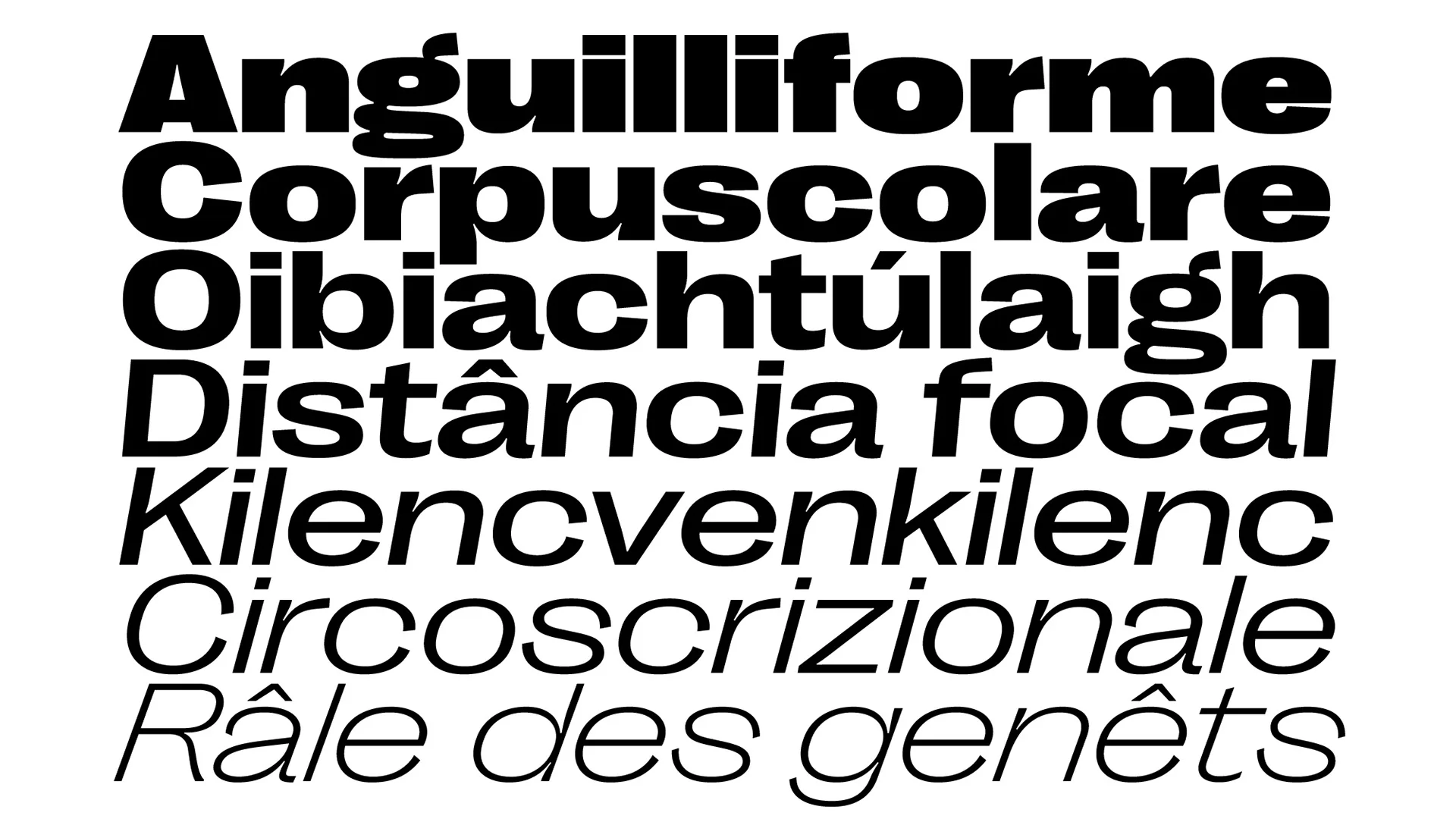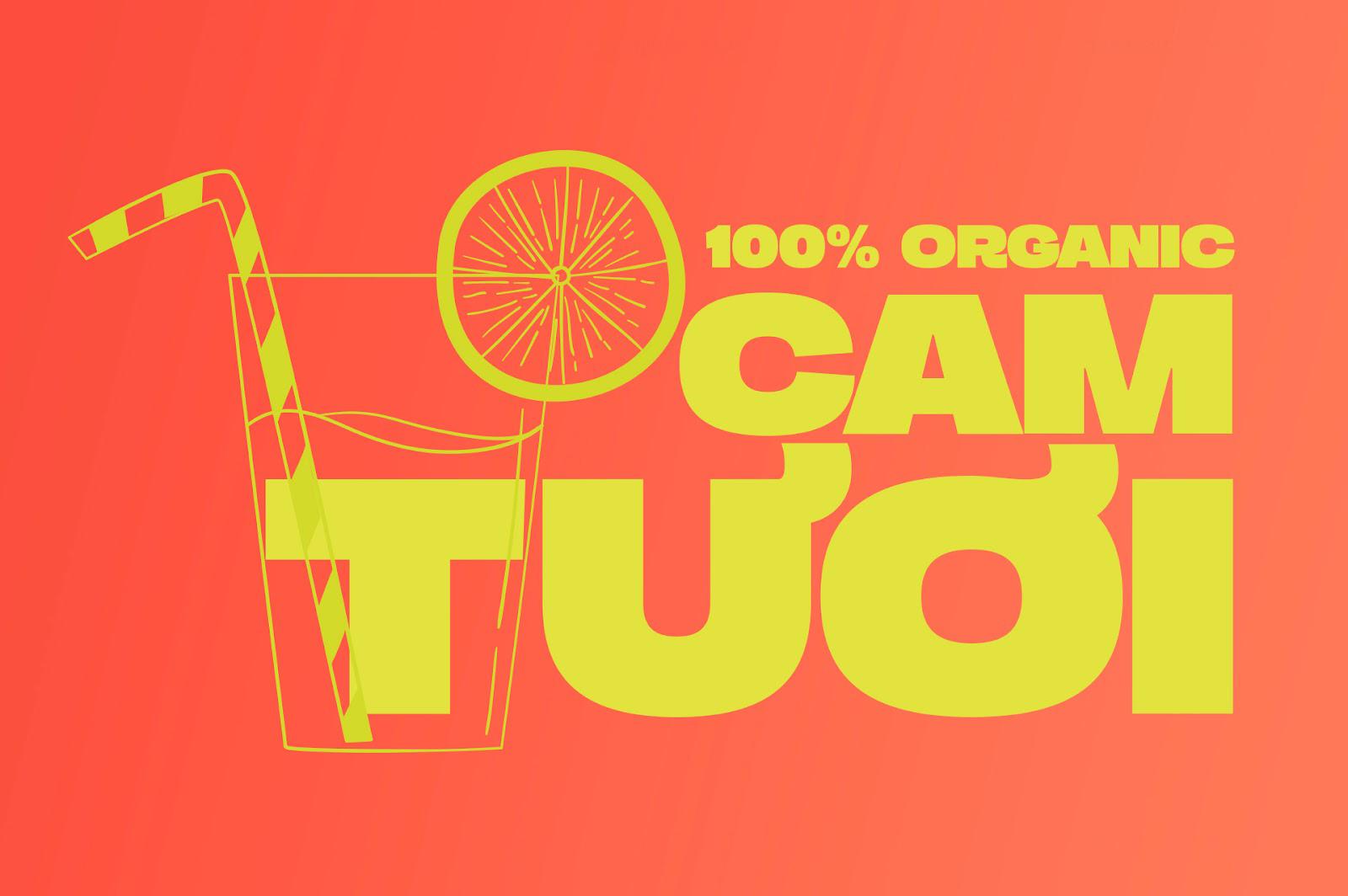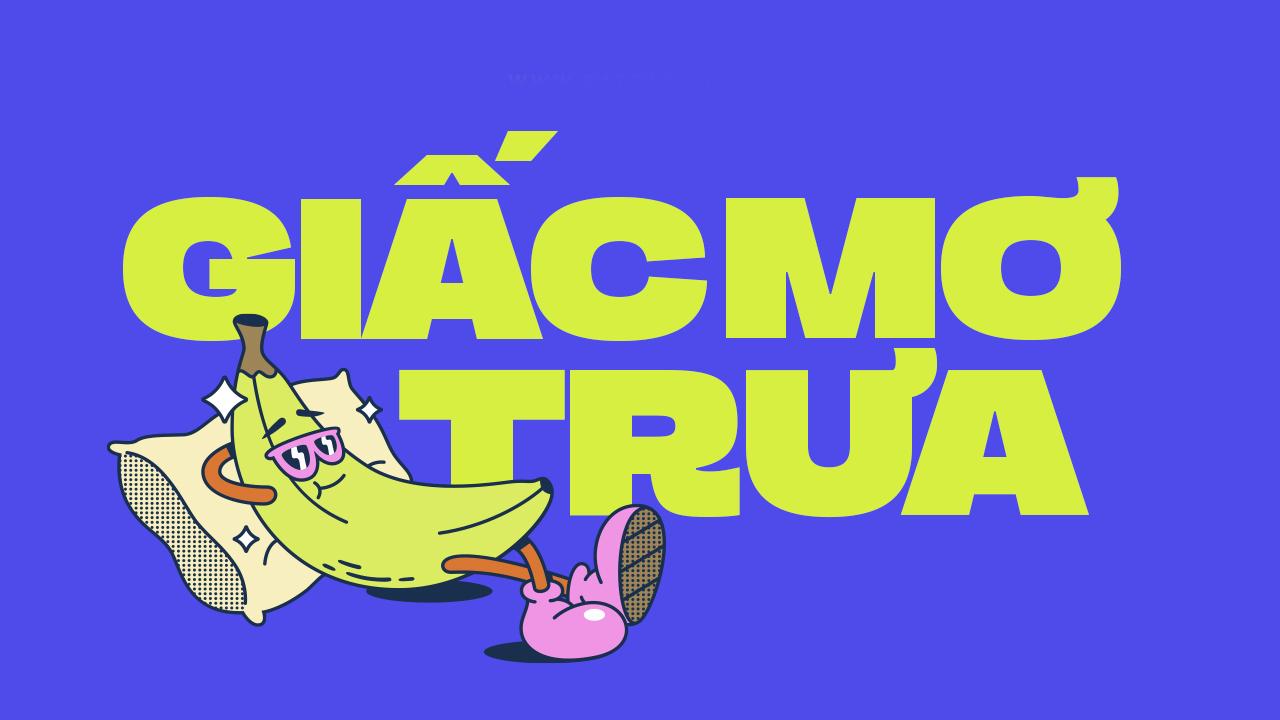
Font Grotesk Việt hóa là bộ phông chữ không chân thuộc nhóm Neo-Grotesque hiện đại, nổi bật với cấu trúc hình học tối giản, các đường nét dứt khoát và tính ứng dụng cực kỳ cao trong thiết kế đồ họa. Trong đó, các biến thể nổi tiếng như Space Grotesk Việt hóa đã trở thành xu hướng được săn đón hàng đầu nhờ những đường cắt vát (ink traps) độc đáo mang đậm hơi thở công nghệ tương lai. Doozypack.vn cung cấp link tải trọn bộ phông chữ Grotesque chuẩn kỹ thuật, giúp bạn sở hữu phông chữ đẳng cấp, hỗ trợ đầy đủ tiếng Việt để tự tin thiết kế bao bì và bộ nhận diện thương hiệu chuyên nghiệp.
Đặc điểm thẩm mỹ độc đáo của bộ font Grotesk & Space Grotesk
Dòng phông chữ Grotesque (không chân đầu thế kỷ 20) luôn mang lại cảm giác mạnh mẽ, minh bạch và thực dụng. Khi được cách tân thành các biến thể hiện đại như Space Grotesk, chúng lại càng trở nên sắc sảo và cá tính hơn.
Phong cách Neo-Grotesque tinh gọn và chuẩn xác
Đặc trưng lớn nhất của Font Grotesk Việt hóa là cấu trúc chữ thẳng đứng vững chãi, tỷ lệ x-height lớn và các nét vẽ có độ dày đồng đều. Phong cách này mang lại sự minh bạch tuyệt đối cho thông tin, giúp người đọc nắm bắt nội dung chỉ trong vài giây. Các phông chữ Grotesque cực kỳ trung tính nhưng không hề nhàm chán, tạo nền tảng vững chắc cho mọi phong cách thiết kế từ tối giản đến phá cách.
Điểm nhấn “Ink Traps” độc đáo trên Space Grotesk
Biến thể Space Grotesk Việt hóa sở hữu chi tiết “bẫy mực” (ink traps) tại các điểm giao nét. Chi tiết kỹ thuật này không chỉ giúp chữ không bị bết mực khi in ấn ở kích thước nhỏ mà còn tạo ra những đường cắt vát vô cùng cá tính, mang lại diện mạo đậm chất công nghệ (Tech/Cyberpunk) cho bao bì sản phẩm.
Ưu điểm nổi bật của bản Font Grotesk Việt hóa
Khi ứng dụng các phông chữ hình học quốc tế vào thị trường trong nước, sự chỉn chu về dấu câu là yếu tố quyết định đến tính chuyên nghiệp của ấn phẩm:
- Khắc phục triệt để lỗi dấu tiếng Việt: Phiên bản Việt hóa đã được đội ngũ thiết kế trau chuốt thủ công từng dấu câu. Các dấu sắc, huyền, hỏi, ngã, nặng được vẽ với tỷ lệ cân đối, đặt ở vị trí thoáng đãng so với thân chữ, không gây cảm giác chắp vá hay đè nét làm mất tính thẩm mỹ.
| Biến thể Font | Đặc điểm thị giác | Ứng dụng đề xuất tại Doozypack.vn |
| Grotesk Light / Regular | Thanh mảnh, thông thoáng, dễ đọc | Dùng cho nội dung hướng dẫn sử dụng, bảng thành phần (Body text). |
| Space Grotesk Bold | Dày dặn, sắc sảo, có ink traps | Dùng làm tiêu đề chính, tên sản phẩm hoặc logo thương hiệu. |
| Grotesk Display | Mạnh mẽ, hiện đại, uy lực | Thiết kế bao bì điện tử, poster sự kiện, túi giấy thời trang. |
03 Ứng dụng thực tế của font Grotesk trong sản xuất bao bì tại Doozypack.vn
Sự hiện đại và sắc sảo của Grotesk mang lại hiệu ứng thị giác đắt giá trên các dòng sản phẩm bao bì thực tế do Doozypack.vn sản xuất:
- Hộp đựng sản phẩm Công nghệ & Phụ kiện thông minh: Nét chữ hình học của Space Grotesk rất tương đồng với thiết kế của các thiết bị điện tử, tạo nên sự đồng bộ chuyên nghiệp từ sản phẩm đến vỏ hộp.
- Bao bì Mỹ phẩm tối giản & Dược mỹ phẩm: Tiêu đề thương hiệu in bằng font Grotesk trên giấy Ivory cán màng mờ tạo cảm giác an toàn, minh bạch và cao cấp.
- Túi giấy doanh nghiệp & Cửa hàng thời trang: Tên thương hiệu in bằng font Grotesk Bold màu đen tối giản trên nền túi giấy trắng giúp khẳng định phong cách hiện đại và đẳng cấp.
Lưu ý kỹ thuật khi in ấn với phông chữ hình học Grotesque
Việc sản xuất bao bì thực tế sử dụng các phông chữ hình học đòi hỏi sự am hiểu kỹ thuật chuyên sâu tại xưởng in Doozypack.vn: